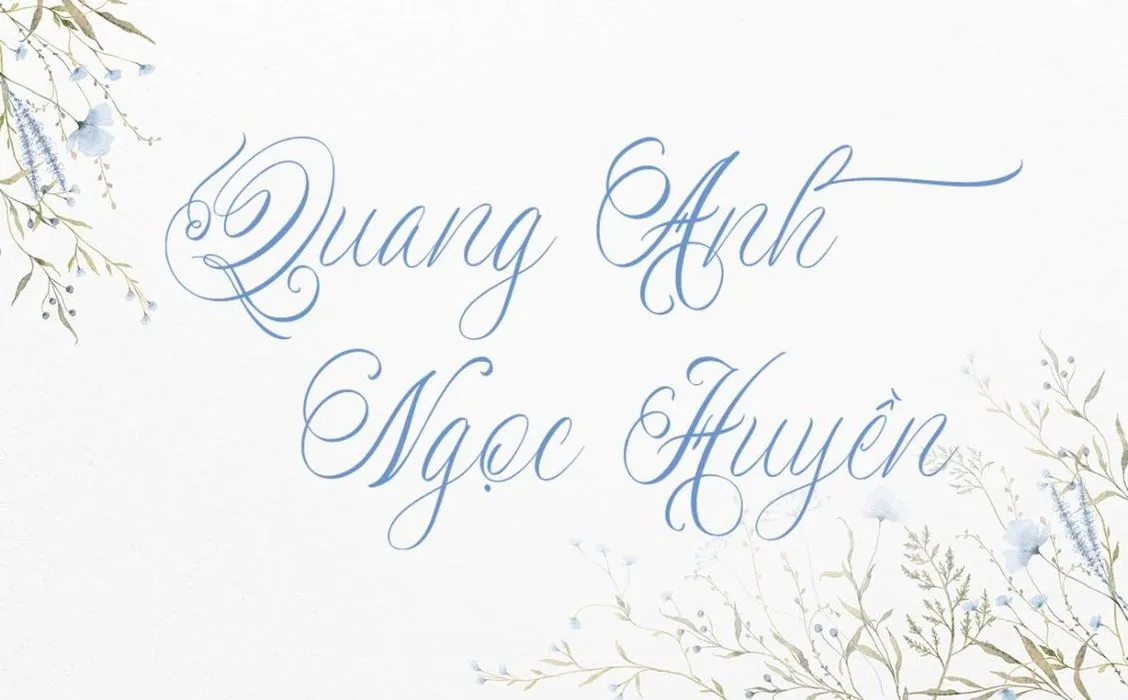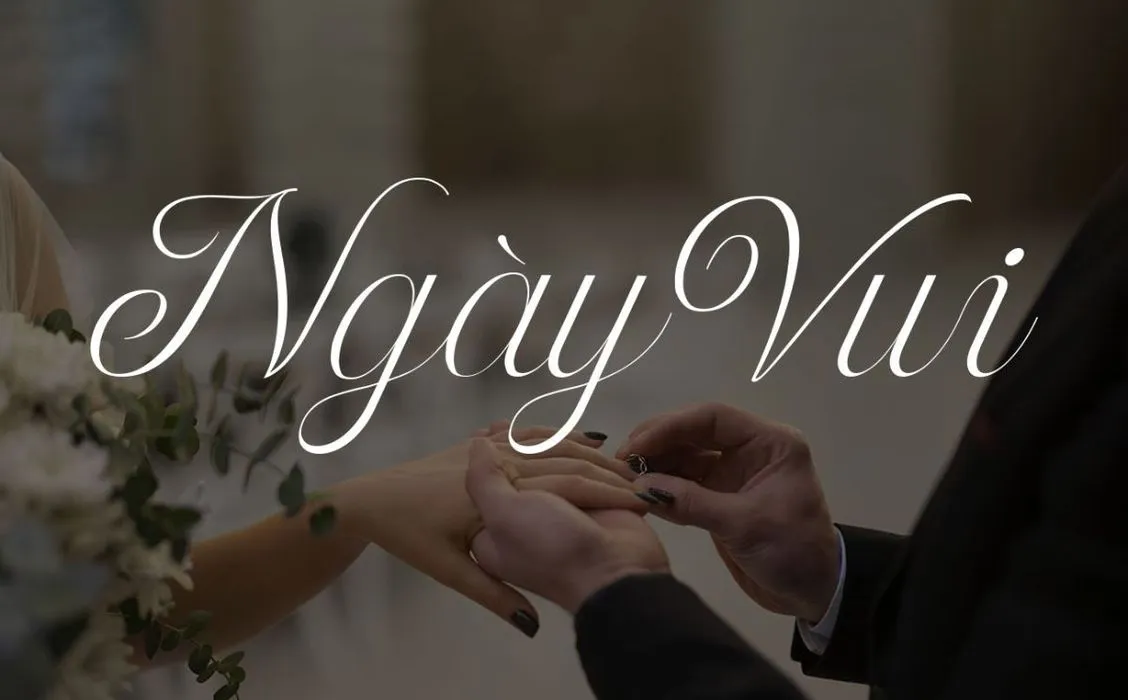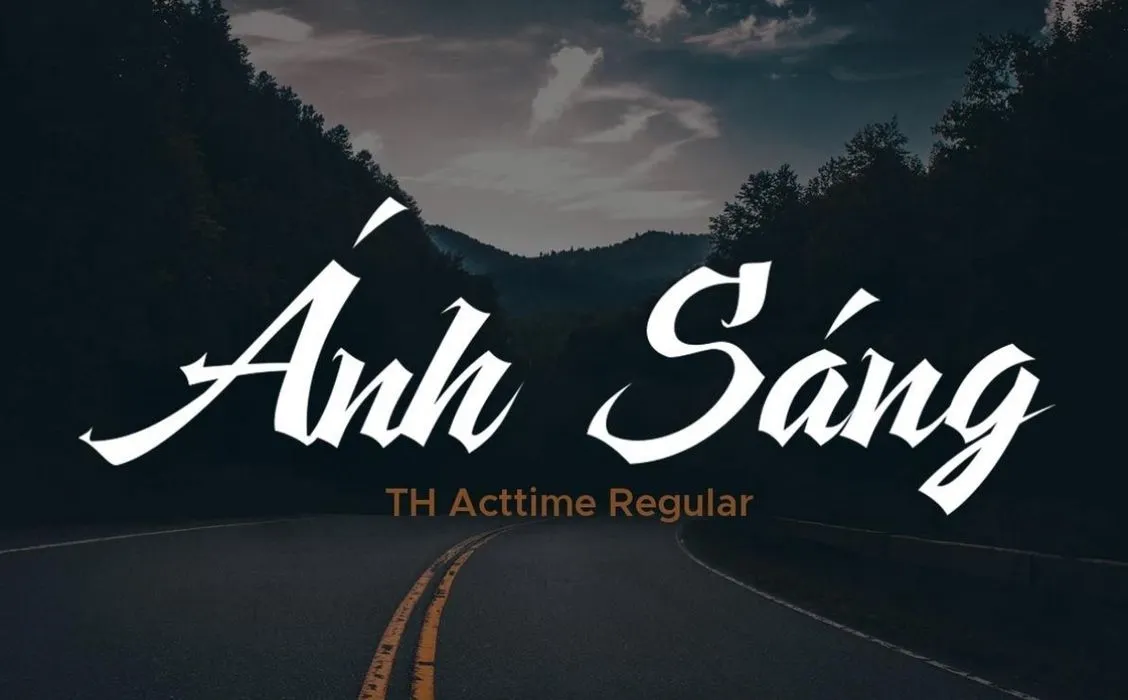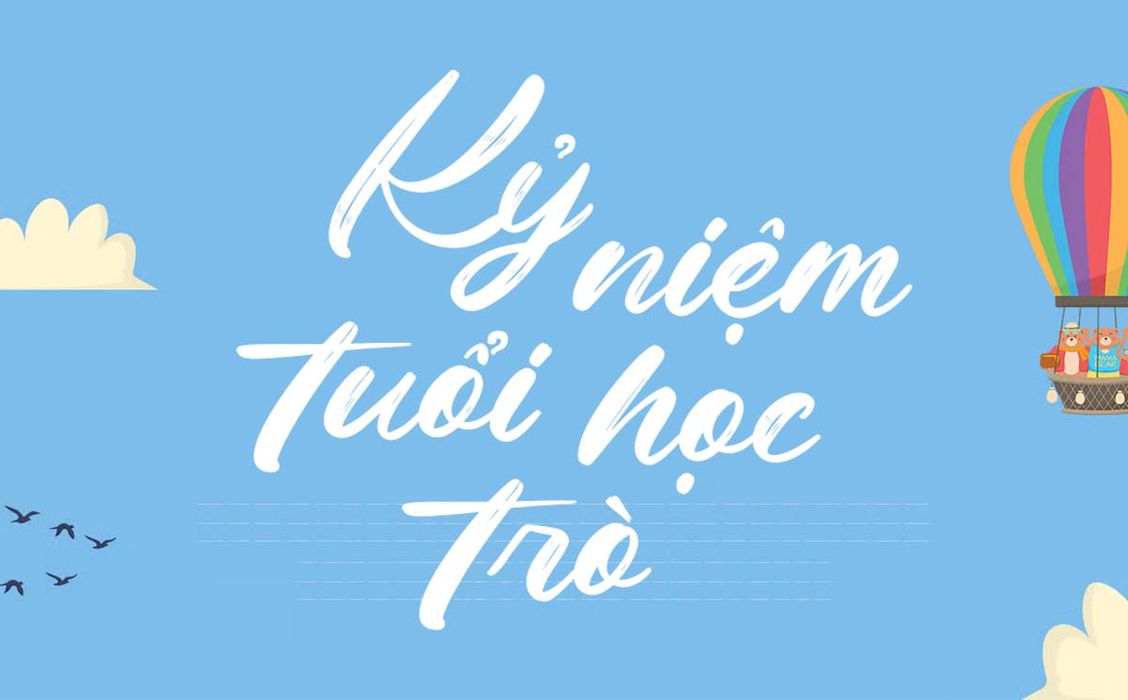
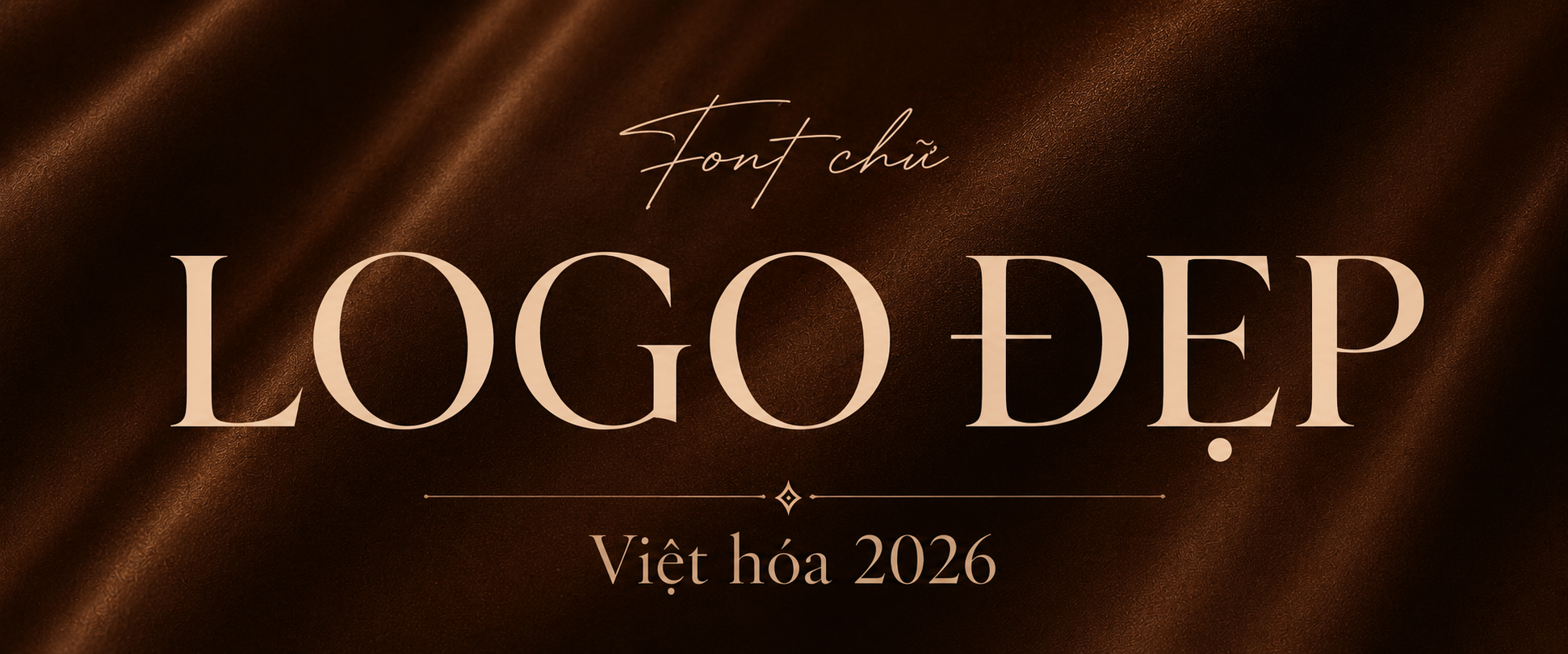
Khi bắt đầu làm logo, nhiều người thường chọn font theo cảm tính: thấy đẹp là dùng. Nhưng với thương hiệu thực tế, đặc biệt là thương hiệu Việt, font logo không chỉ cần đẹp mà còn phải đọc rõ, có dấu tiếng Việt ổn, dễ triển khai trên avatar, bao bì, bảng hiệu, website và cả social media. Đây cũng là lý do nhu cầu tìm font chữ logo đẹp Việt hóa ngày càng tăng trong năm 2026.
Font dùng cho logo khác với font dùng cho poster hay banner. Một font tiêu đề có thể gây ấn tượng mạnh ở kích thước lớn, nhưng khi thu nhỏ lên avatar Facebook, favicon website hoặc tem nhãn sản phẩm thì lại mất chi tiết, khó đọc hoặc vỡ tinh thần thương hiệu. Ngược lại, một font quá an toàn có thể dễ đọc nhưng không đủ cá tính để tạo nhận diện.
Nhu cầu tìm kiếm từ khóa font chữ logo thường rơi vào ba nhóm:
Người cần làm logo mới cho cửa hàng, doanh nghiệp hoặc thương hiệu cá nhân.
Designer cần kho font Việt hóa để dựng nhiều concept theo từng ngành.
Chủ shop muốn chỉnh nhanh template logo, bao bì, card visit, poster mà không mất thời gian xử lý lỗi dấu tiếng Việt.
Điểm quan trọng nhất ở thị trường Việt Nam là khả năng Việt hóa. Một logo có thể chỉ dùng chữ cái Latin khi đặt tên thương hiệu, nhưng hệ thống nhận diện đi kèm vẫn cần slogan, mô tả ngắn, menu, tên sản phẩm hoặc phiên bản trình bày có dấu. Vì vậy, dùng font Việt hóa ngay từ đầu sẽ giúp quá trình mở rộng bộ nhận diện mượt hơn nhiều.
Tiêu chí chọn font chữ logo phù hợp với các tiêu chuẩn sau:
Trước khi chọn font, hãy trả lời thương hiệu của bạn muốn được nhớ đến như thế nào:
Sang trọng, tin cậy, cao cấp
Tối giản, hiện đại, công nghệ
Mềm mại, nữ tính, cảm xúc
Cá tính, nổi bật, trẻ trung
Truyền thống, thủ công, bản sắc
Mỗi nhóm tính cách sẽ hợp với một cấu trúc chữ khác nhau. Serif thường tạo cảm giác chỉn chu và cao cấp. Sans-serif thiên về hiện đại, rõ ràng. Script và signature phù hợp tính cá nhân, cảm xúc. Display hoặc brush mạnh ở khả năng gây chú ý, thích hợp với thương hiệu cần sự bùng nổ thị giác.
Một font logo đẹp trên mockup chưa chắc đẹp ngoài đời thực. Hãy kiểm tra:
Khi đặt ở kích thước nhỏ trên avatar, icon app hoặc watermark
Khi in trên tem nhãn, bao bì, card visit
Khi đặt trên nền sáng, nền tối và ảnh nền phức tạp
Nếu nét chữ quá mảnh, quá nhiều chi tiết trang trí hoặc khoảng cách ký tự không ổn, logo sẽ khó dùng lâu dài.
Đây là tiêu chí cực kỳ quan trọng. Nhiều font quốc tế nhìn rất đẹp nhưng khi thêm dấu tiếng Việt lại bị lệch vị trí, nặng đầu chữ hoặc làm hỏng nhịp điệu tổng thể. Với thương hiệu Việt, bạn nên ưu tiên font đã được Việt hóa tốt để bảo đảm tính nhất quán trong mọi ứng dụng sau này.
Logo hiếm khi chỉ có mỗi chữ. Thông thường bạn sẽ còn kết hợp:
Biểu tượng
Tagline
Màu nhận diện
Bộ bài đăng social
Bao bì hoặc biển hiệu
Vì vậy, font logo nên có khả năng đứng độc lập nhưng cũng phải “ăn nhập” với toàn bộ hệ thống visual. Font quá đặc trưng có thể đẹp lúc đầu nhưng khó mở rộng về sau.
Một số font có nhiều weight hoặc style sẽ hữu ích hơn rất nhiều khi làm thương hiệu. Bạn có thể dùng bản bold cho wordmark, bản regular cho tagline, bản light cho nội dung hỗ trợ. Những font family linh hoạt thường giúp bộ nhận diện trông chuyên nghiệp và đồng bộ hơn.
Dưới đây là các nhóm font và tài nguyên nổi bật đang xuất hiện trên danh mục Font S99. Mình chọn theo định hướng “dùng được cho logo”, tức là vừa có tính nhận diện, vừa có khả năng ứng dụng thực tế.
Nếu thương hiệu của bạn cần cảm giác tinh tế, đáng tin và premium, serif là nhóm nên xem đầu tiên. Trên S99, có rất nhiều font phù hợp với brand mỹ phẩm, studio thời trang, cửa hàng phụ kiện, spa cao cấp hoặc nhãn hàng handmade thiên về sự thanh lịch. Đây là một số mẫu font tiêu biểu trên s99.vn
Font TH Selvia Genatu - Link tải
Font TH Retalin Regular - Link tải
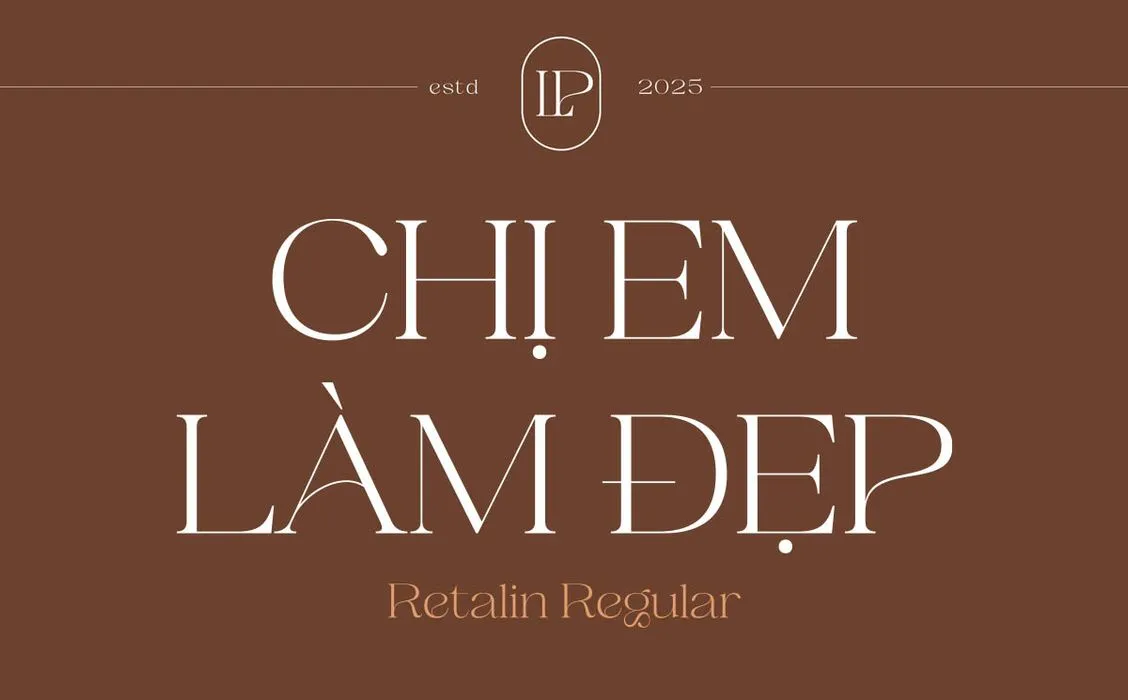
Điểm mạnh của nhóm này là tạo cảm giác “đắt”, có chiều sâu thị giác và hợp khi đặt trên bao bì, name card, lookbook. Tuy nhiên, bạn nên tránh chọn serif quá nhiều nét nhỏ nếu logo cần hiển thị ở kích thước rất bé.
Nếu bạn muốn logo gọn gàng, dễ đọc, hiện đại và dùng bền trong nhiều bối cảnh, sans-serif là lựa chọn an toàn nhưng vẫn hiệu quả. Trên S99 hiện có các mẫu như
Một font chữ logo đẹp Việt hóa không chỉ giúp logo trông bắt mắt mà còn quyết định cảm giác thương hiệu, độ chuyên nghiệp và khả năng triển khai lâu dài. Năm 2026, xu hướng không còn là chọn font “đẹp chung chung”, mà là chọn font đúng ngành, đúng tính cách thương hiệu và đúng bối cảnh sử dụng.